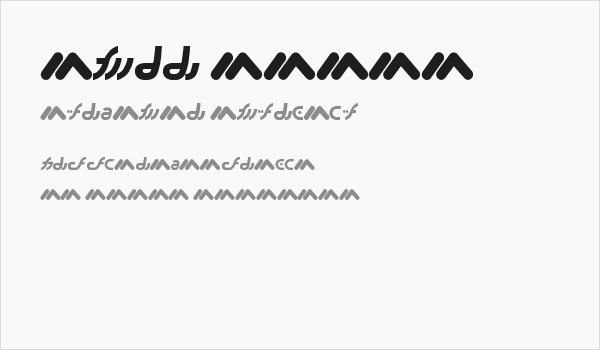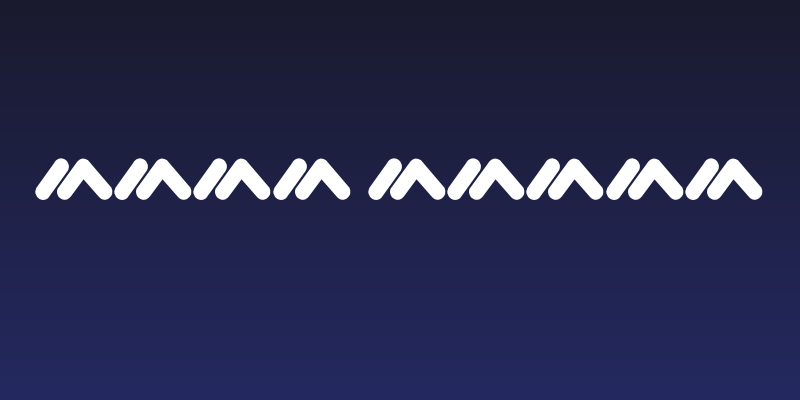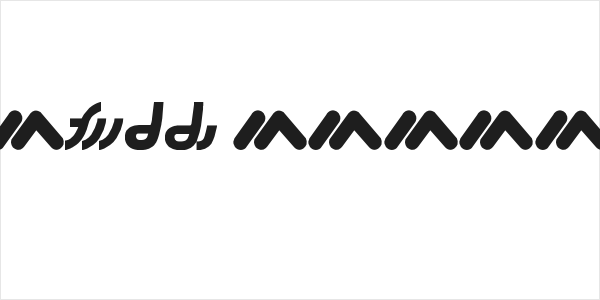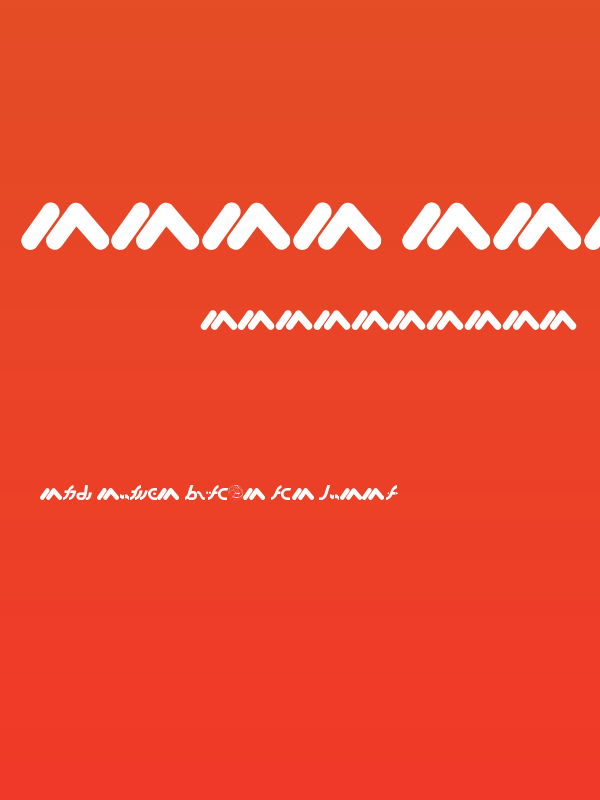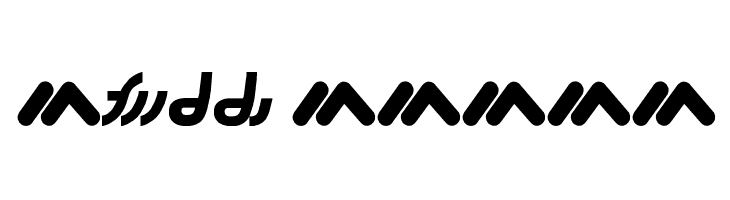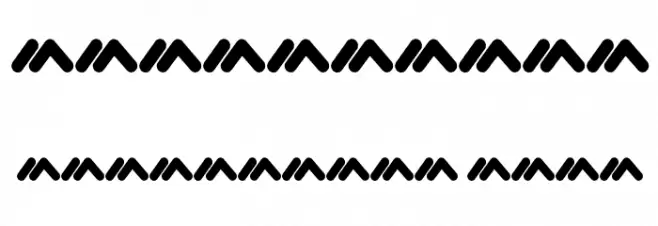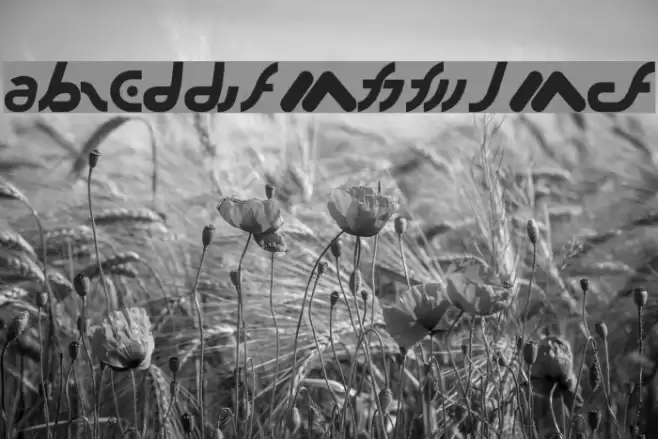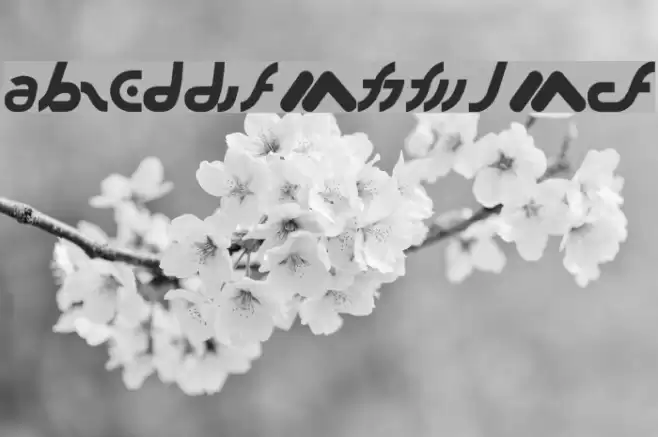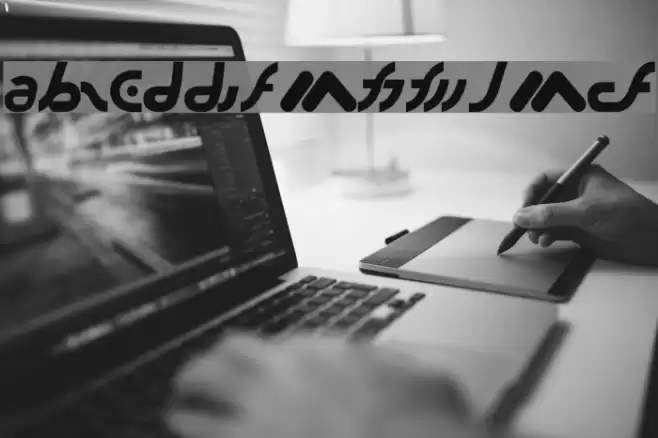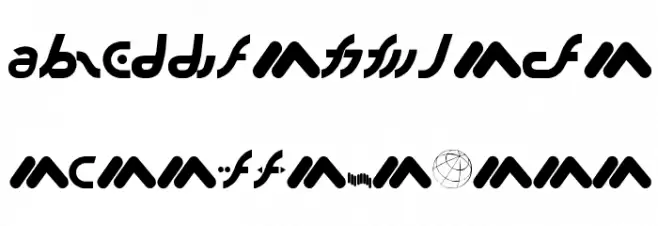
Lide 106.9 Font
| Stil general | Futuristic, Abstract |
| Caz de utilizare | Logos, Artistic displays, Experimental design |
| Proiecte propuse | Ideal for experimental design projects, futuristic branding, abstract art pieces, and creative digital media. |